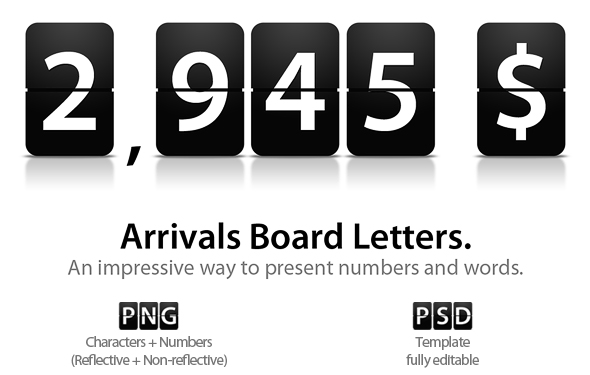
Font: Lettere dall'aereoporto (PNG & PSD)
Molto divertente questa risorsa grafica che “simula” le lettere dei tabelloni degli aeroporti, ma che spesso abbiamo ammirato anche sul sito della Apple in occasione di countdown per avvenimenti importanti.
Molto divertente e molto carino sì, ma anche molto utile per creare messaggi importanti per le homepage dei nostri siti e per di più molto semplici da usare grazie alle 4 versioni a disposizione!
Il font usato è: “Myriad Pro Semibold”